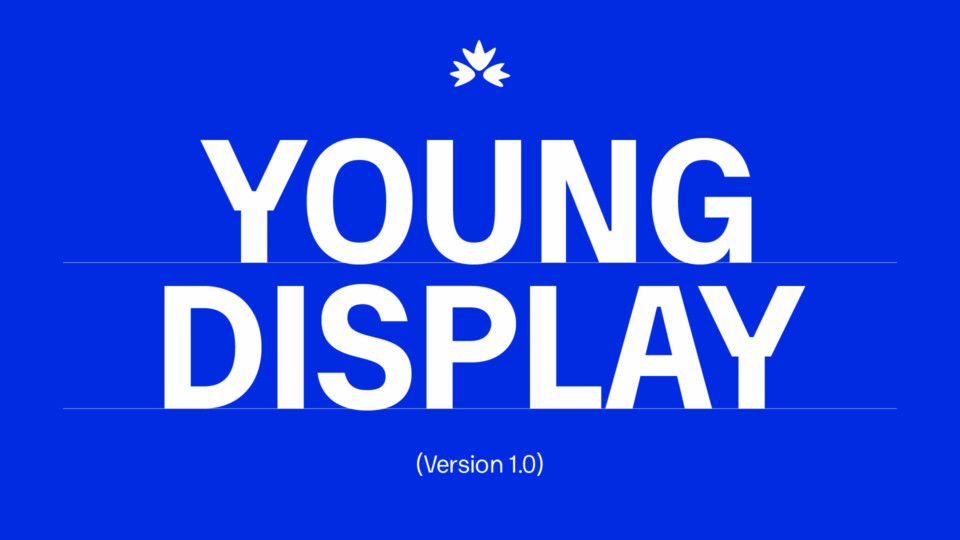
Tải Font Tiếng Việt Young Display Miễn Phí Cho Thiết Kế Sáng TạoGiới thiệu về Font Tiếng Việt Young DisplayTrong thế giới thiết kế đồ họa hiện đại, việc lựa chọn một bộ Font Miễn Phí phù hợp đóng vai trò quyết định đến sự thành công của một tác phẩm. Nếu bạn đang tìm kiếm một phong cách phá cách, năng động và tràn đầy năng lượng trẻ trung thì Font Tiếng Việt Young Display chính là câu trả lời hoàn hảo. Đây là bộ phông chữ được tối ưu hóa đặc biệt, giúp các bạn học sinh và thầy cô dễ dàng ứng dụng vào bài giảng.Những đặc điểm nổi bật của phông chữThiết kế hiện đại và phá cáchBộ chữ sở hữu đường nét dày dặn, các góc bo tròn mềm mại kết hợp cùng những nét cắt táo bạo. Điều này tạo nên một tổng thể vừa tinh nghịch, vừa mang đậm tinh thần nghệ thuật đương đại, giúp các tiêu đề lớn trở nên nổi bật hơn bao giờ hết.Hỗ trợ tiếng Việt hoàn chỉnhĐiểm cộng lớn nhất của bộ phông này là đã được việt hóa chỉn chu. Người dùng sẽ không còn gặp lỗi font, lỗi dấu khi gõ các văn bản tiếng Việt phức tạp, đảm bảo tính thẩm mỹ cao nhất cho mọi sản phẩm đồ họa.Ứng dụng thực tế trong học tập và giảng dạyLàm slide thuyết trình ấn tượngHọc sinh có thể dùng phông chữ này để thiết kế slide PowerPoint, giúp bài thuyết trình nhóm thêm phần sinh động và thu hút sự chú ý của thầy cô lẫn bạn bè trong lớp.Thiết kế báo tường và poster trường họcCác câu lạc bộ hoặc ban chấp hành đoàn trường sẽ có thêm một lựa chọn tuyệt vời để làm ban rôn, poster sự kiện hoặc trang trí báo tường nhân ngày lễ lớn.Kết luận và tải vềBộ phông chữ này thực sự là công cụ đắc lực cho những ai yêu thích sự sáng tạo và đổi mới. Hãy truy cập ngay Font Miễn Phí, Font Việt Hóa, Font Tiếng Việt Young Display để tải về và trải nghiệm tạo nên những tác phẩm độc đáo nhất.
Font Tiếng Việt Young Display